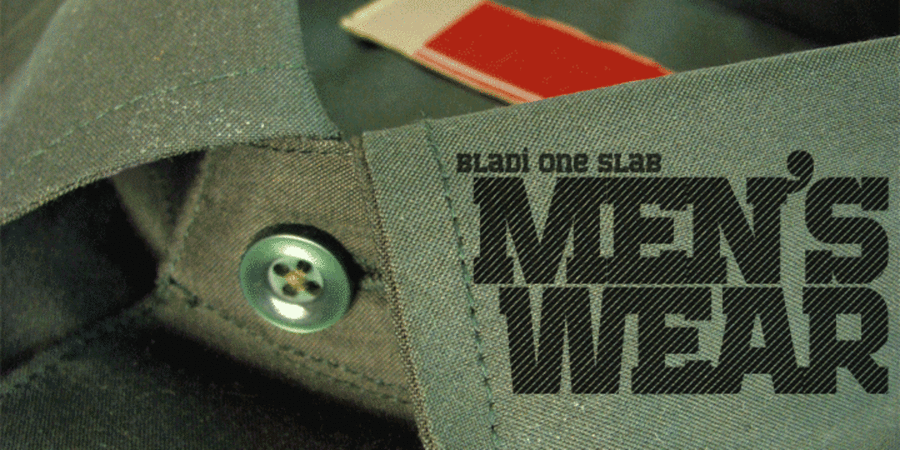
Bladi One Slab 4F (12 шрифтів)
Опис гарнітури Bladi One Slab 4FСамый мужественный брусковый шрифт для заголовков и плакатов. Он настолько суров, что выдерживает прямое попадание противотанковой ракеты. Разработан Сергеем Ткаченко в 2009 году.
Особливості сімейства шрифтів Bladi One Slab 4FХіт десятиліття:
Асоціації з сімейством шрифтів Bladi One Slab 4FОсобистість і характер гарнітури:
сильний, потужний, техногенний, важкий, твердий, жорсткий, гострий, сталевий, індустріальний, мужній, стійкий, статичний, міцний, значний, переконливий, авторитетний, наполегливий, рівний, чіткий, якісний, дзвінкий, прямокутний, серйозний, залізний, надійний, впевнений, військовий, армійський, солдатський, відповідальний, суворий, квадратний, точний, логічний, автоматичний, різкий, міський, машинний, інженерний, урбаністичний, промисловий, грізний, грубий, гучний, кондовий, сміливий, важливий, монументальний, тоталітарний, стабільний, робочий, мотивуючий, тісний, крутий, агресивний, залізничний, амбітний, брутальний, ігровий, радикальний, рубаний, запальний, чорний, помітний, яскравий, активний, нахабний
металургія, машинобудування, техніка, війна, танк, інструмент, будматеріали, будівництво, камінь, бетон, верстат, бодібілдинг, тренажери, завод, індустрія, промисловість, електростанція, енергетика, джинси, армія, ремонт, охорона, захист, страйкбол, блокбастер, бойовик, екшен, взуття, конструктор, креслення, архітектура, інженер, автоматика, урбаністика, Місто, авто, робот, гра, зброя, тара, склад, порт, ящик, патрони, депо, шолом, уніформа, вагон, автомат, шутер, спорт, екскаватор, позашляховик, шахта, шахтар, регбі, цегла, вантажівка, далекобійник, сталевар, мотор, двигун, залізо, технології, залізниця, робочий, кубики, лего, кіберспорт, Локдаун, комп'ютерна гра, нафта, селфі, поліція, екстрим, каскадер Гарнітура асоціюється з віком: